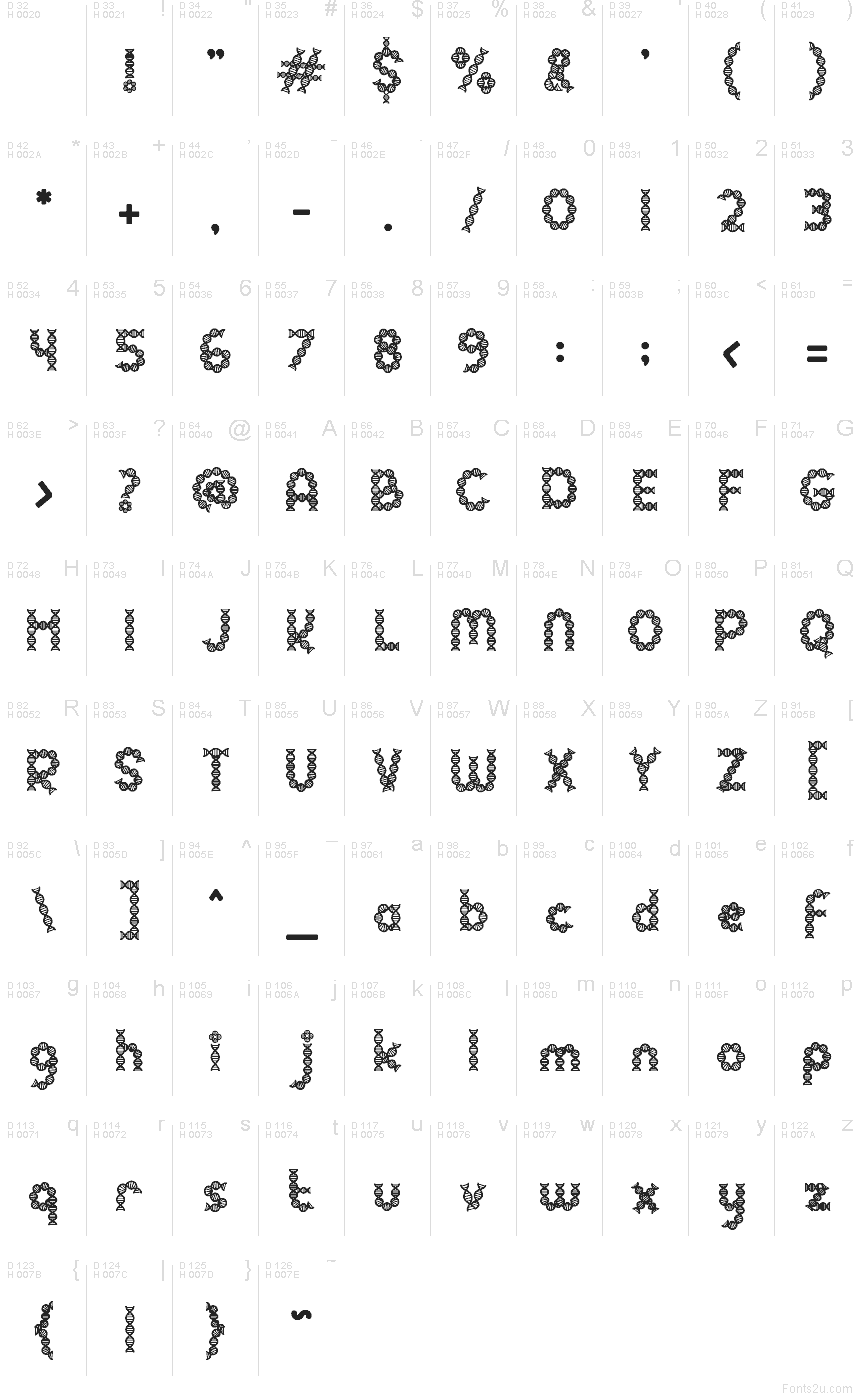
Clever Science Dna
Clever Science Dna von Putracetol Studio ist eine kostenlose, wissenschaftlich inspirierte Display-Schrift, die aus handgezeichneten DNA-Helices und kleeblattartigen Zellformen besteht. Die Buchstaben wirken wie verspielte Labor-Embleme – mit geschwungenen Konturen, gestreiften Innenflächen und einer skizzenhaften Linienführung, die das Set eher wie eine Illustration als eine klassische Typografie erscheinen lässt.
Damit ist diese kostenlose Schriftart die ideale Wahl für STEM-Veranstaltungsplakate, Arbeitsblätter im Unterricht, Science-Fair-Projekte, Kinderbuchcover oder Museumsbeschilderungen, bei denen das Alphabet selbst zum Thema wird. Sie eignet sich zudem hervorragend für kurze Überschriften und Initialen im Monogramm-Stil, da das wiederkehrende Helix-Muster selbst einem einzelnen Buchstaben den Charakter eines kleinen Biologie-Abzeichens verleiht.